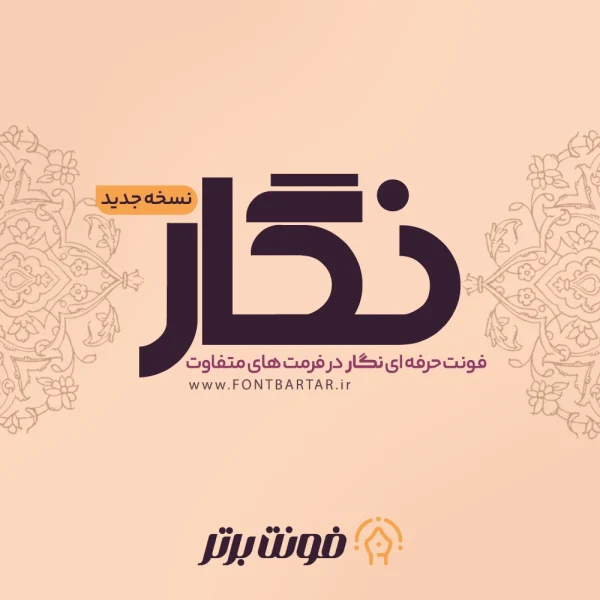
فونت فارسی نگار
فونت فارسی تگار یک فونت بسیار زیبا و شاد که تا مدتها میتواند نیاز شما به یک قلم اصلی برای کارهای تیتر و توضیحی و غیره بر طرف کند. این قلم را میتوانید در کارت ویزیت ، پوستر ، تابلوهای سردرمغازه ها ، کارهای تبلیغاتی و غیره به راحتی استفاده نمایید .
فونت نگار به سبکی طراحی شده که می توان در هر مضمونی تایپوگرافی ،لوگو تایپ،تبلیغات محیطی یا در معرفی محصول خاص و… از آن بهره برد فونت گلاب پتانسیل ویرایش را نیز دارد شما می توانید با کمی خلاقیت در نرم افزار های فتوشاپ یا ایلوستریتور از این فونت طرح های خلاقانه و زیبا اجرا کنید.
فونت نگار دارای چند وزن است؟
- این فونت در یک وزن می باشد.
فونت نگار از چه زبان هایی پشتیبانی می کند؟
- از یک زبان فارسی را پشتیبانی می کند.
مزایای استفاده از فونت نگار:
- ترکیب فوق العاده حروف برای طراحی